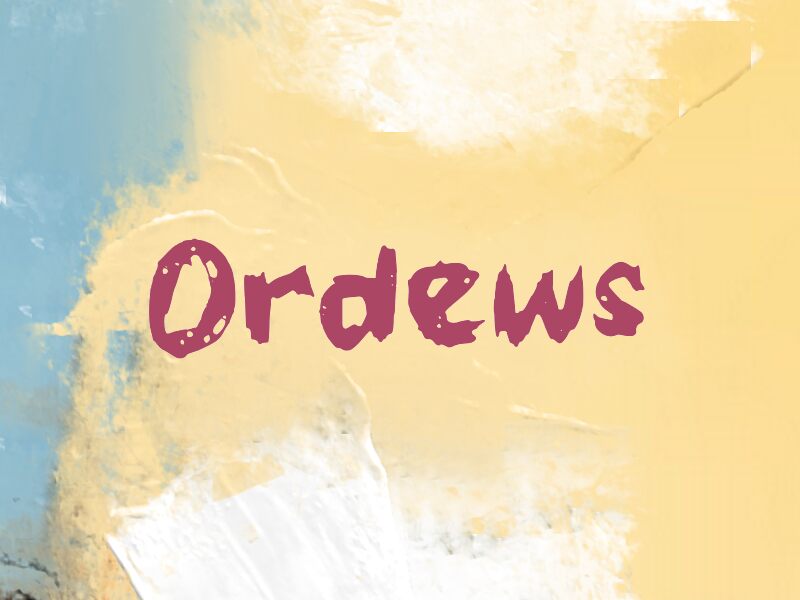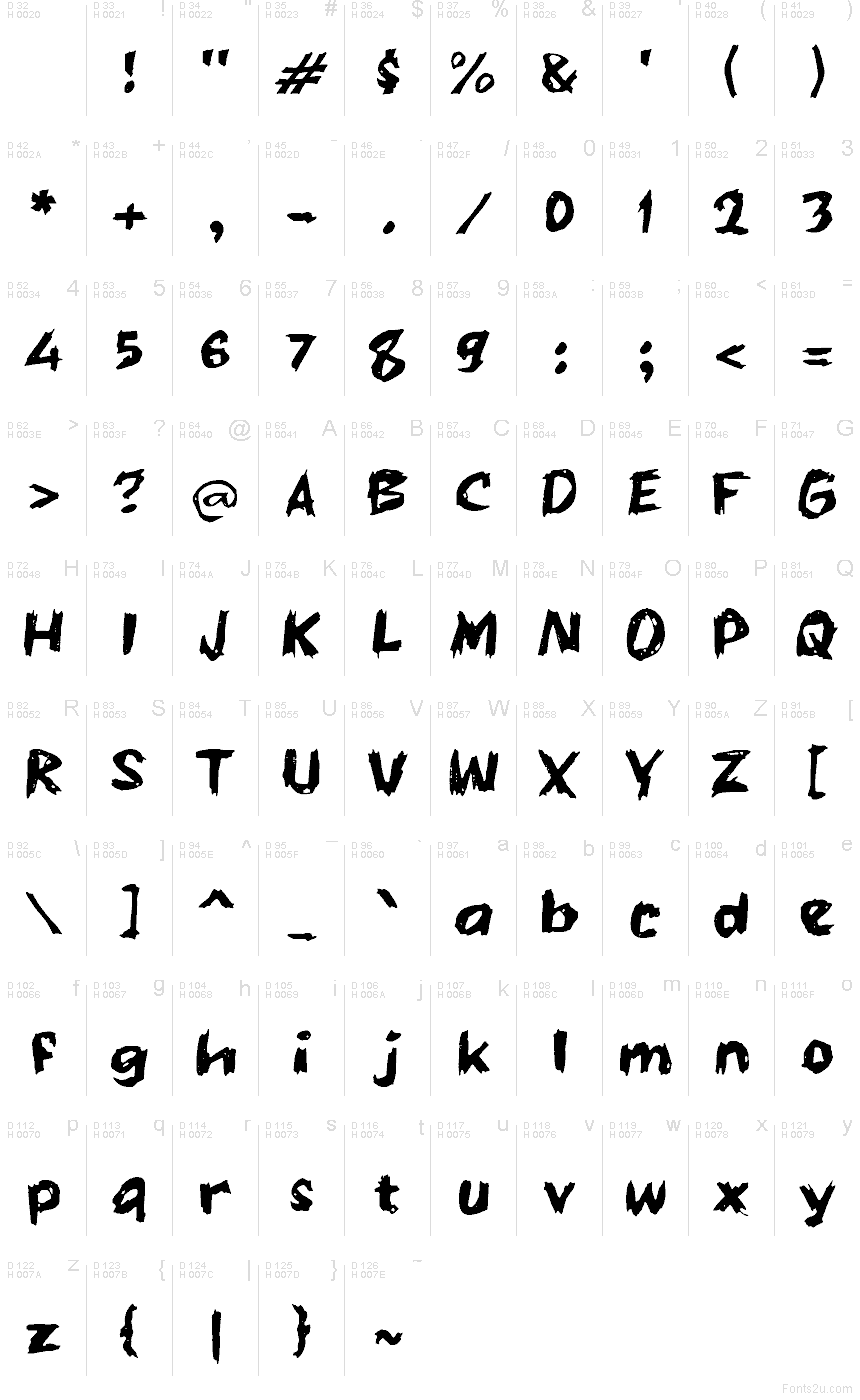
Ordews
Ordews od Wep je bezplatné display písmo v trash štýle, ktoré zaujme svojimi roztrhanými, amorfnými siluetami a nerovnomernými medzerami, vďaka ktorým každé písmeno pôsobí ako rozožraté zvnútra. Drsnosť pôsobí ako súčasť konštrukcie, nie len ako povrchový efekt, čo dodáva písmenám rozmazané a otrhané hrany, ktoré zostávajú konzistentné v celom dizajne.
Táto textúra dodáva krátkym nadpisom správny „špinavý“ nádych, ideálny pre punkové letáky, hororové plagáty, undergroundové ziny, herné headery či obaly s efektom opotrebovania. Keďže tvary pripomínajú skôr poškodené výstrižky než úhľadné písmo, Ordews najlepšie vynikne tam, kde sú šum, oderky a zámerne neupravený vzhľad súčasťou konceptu.